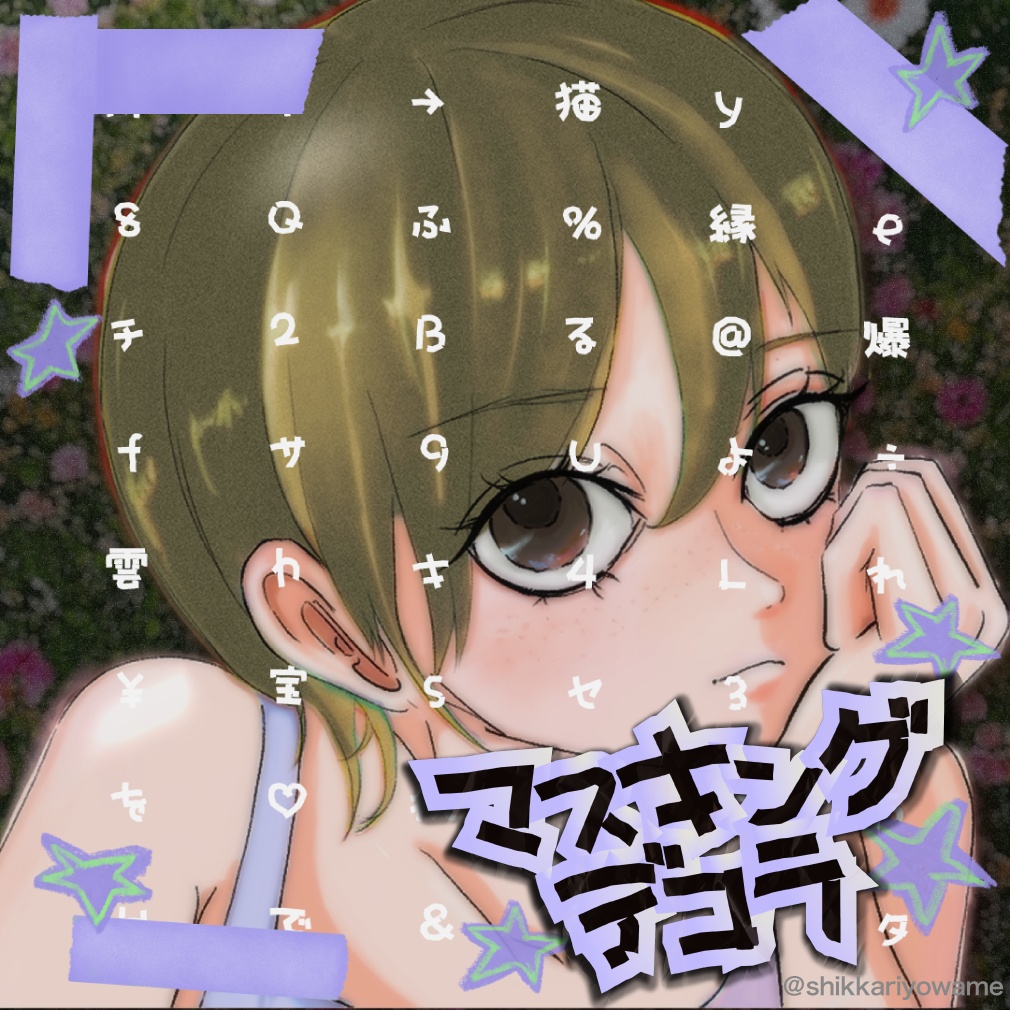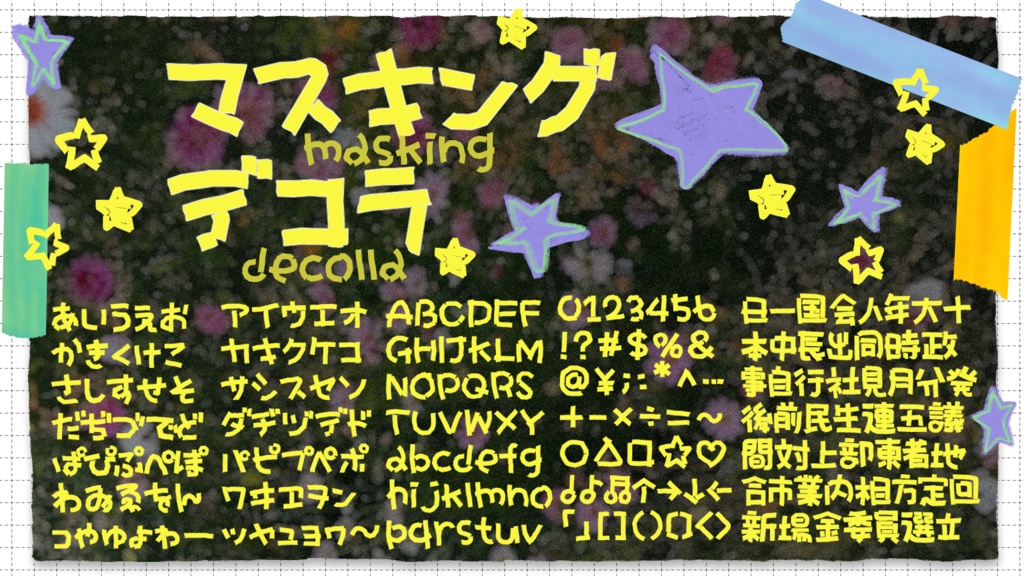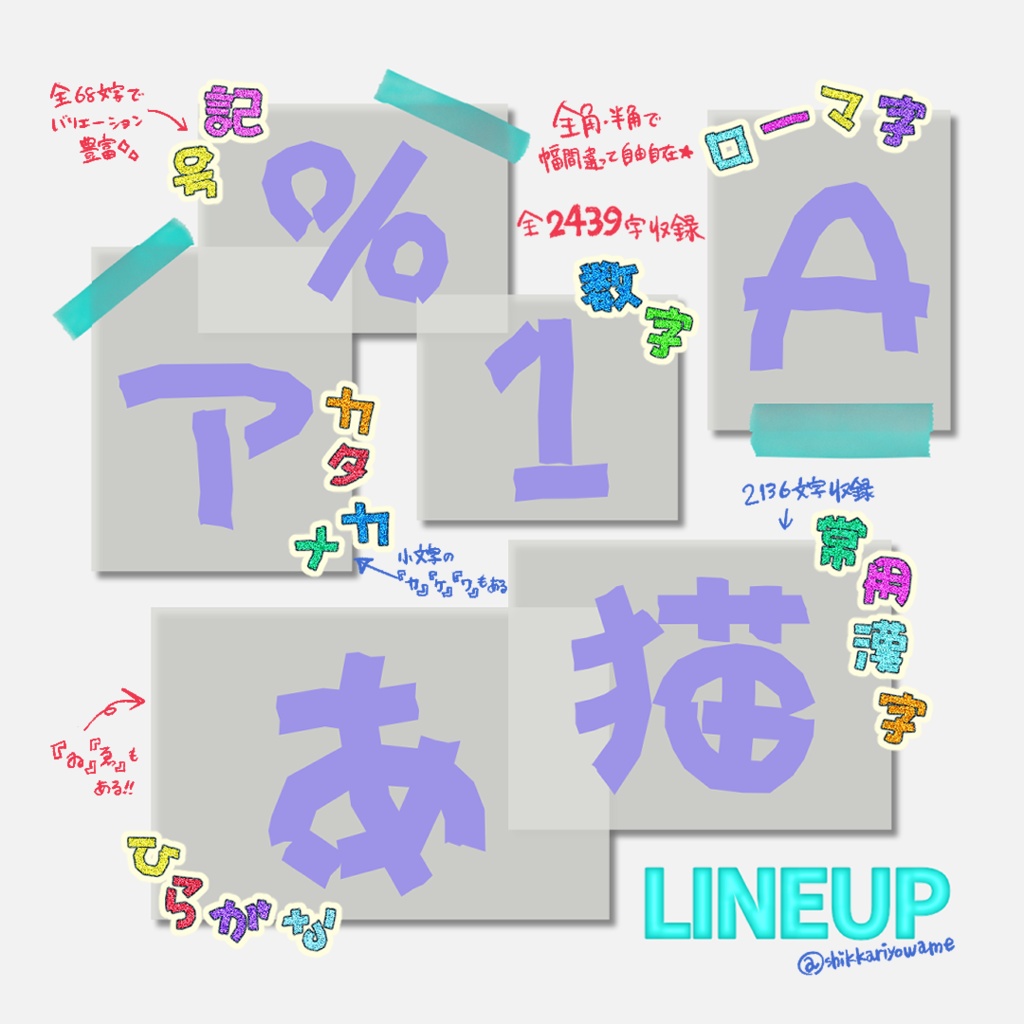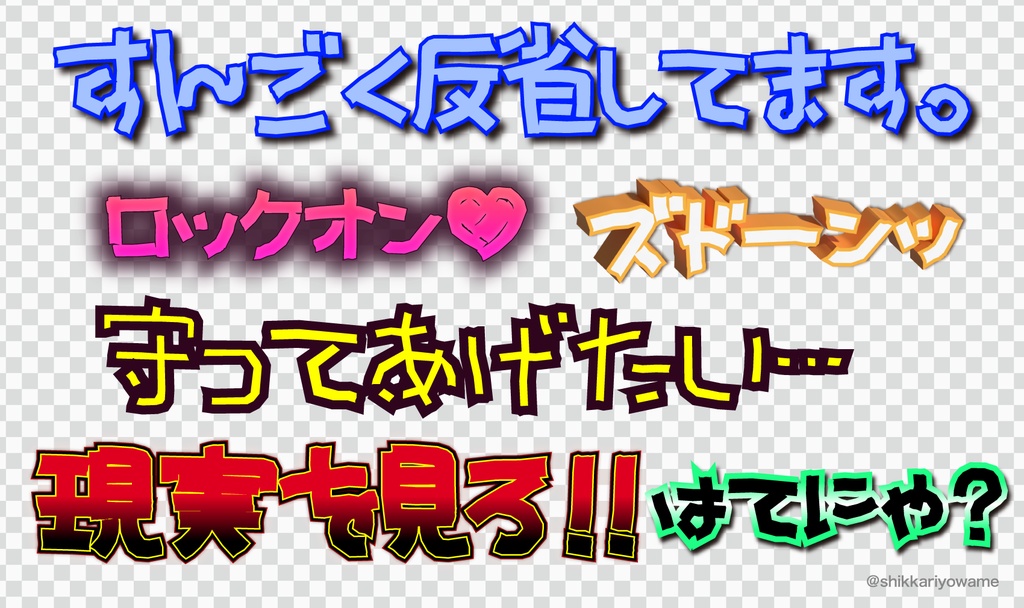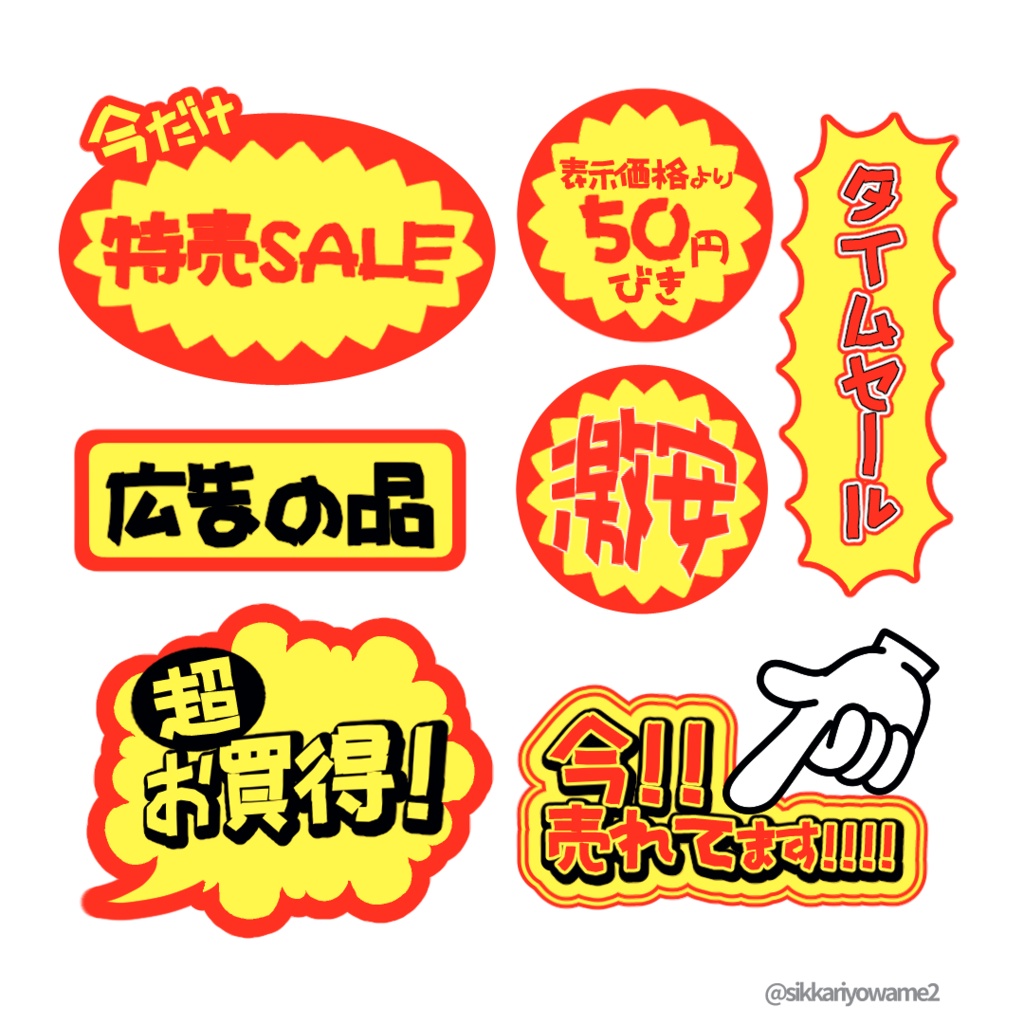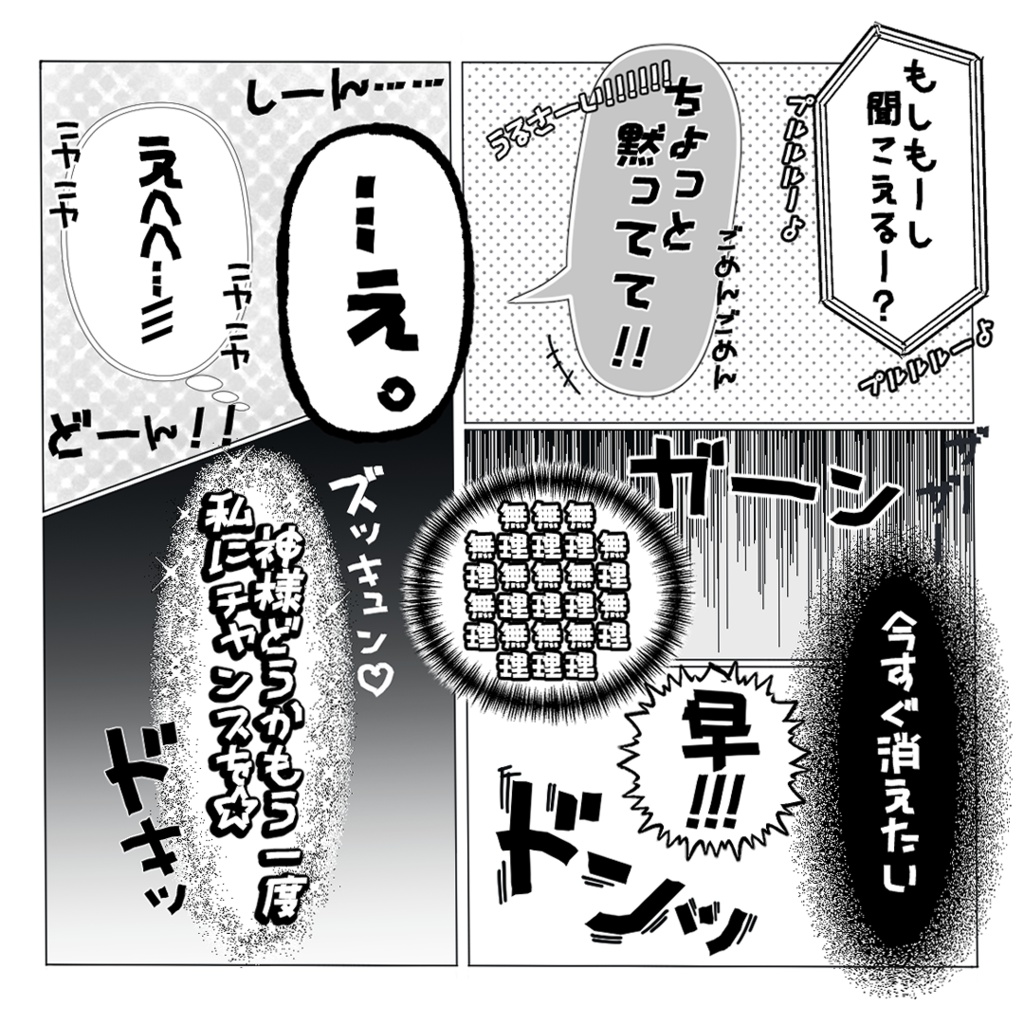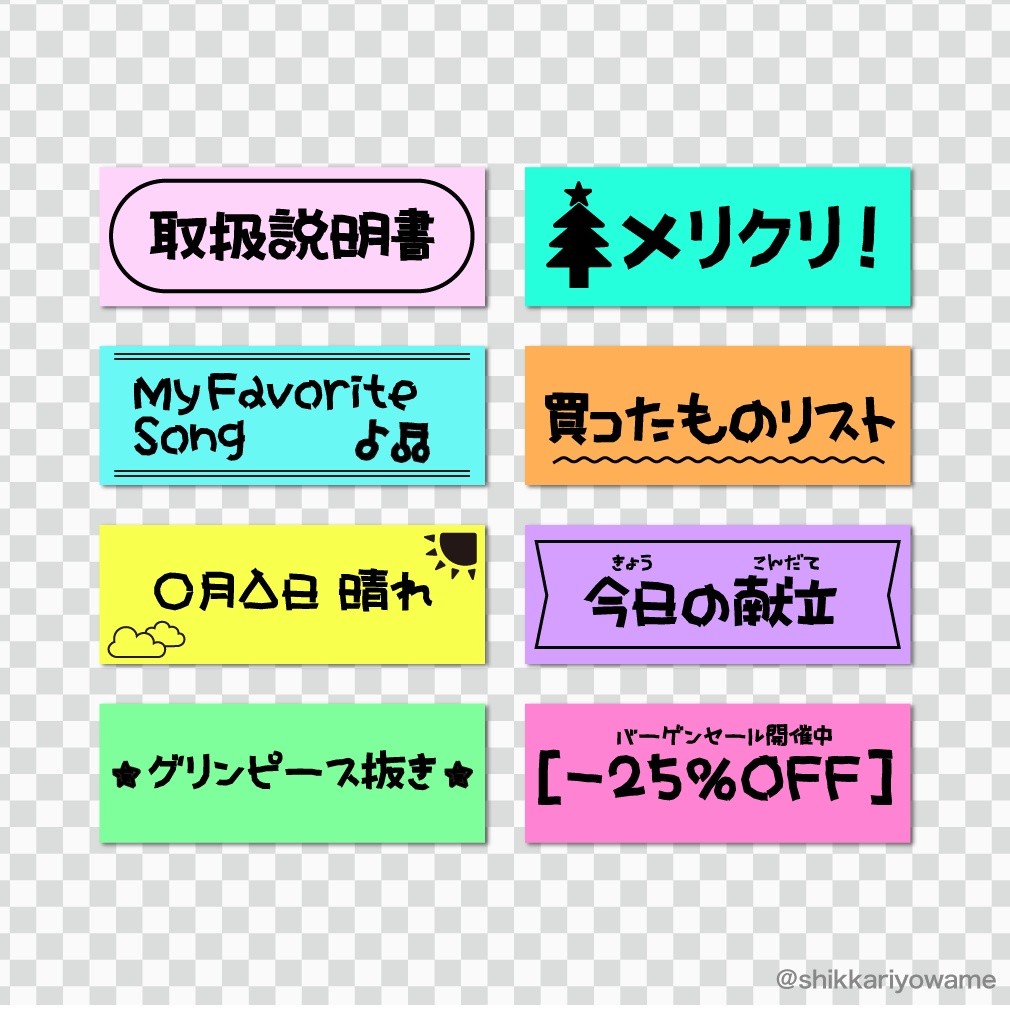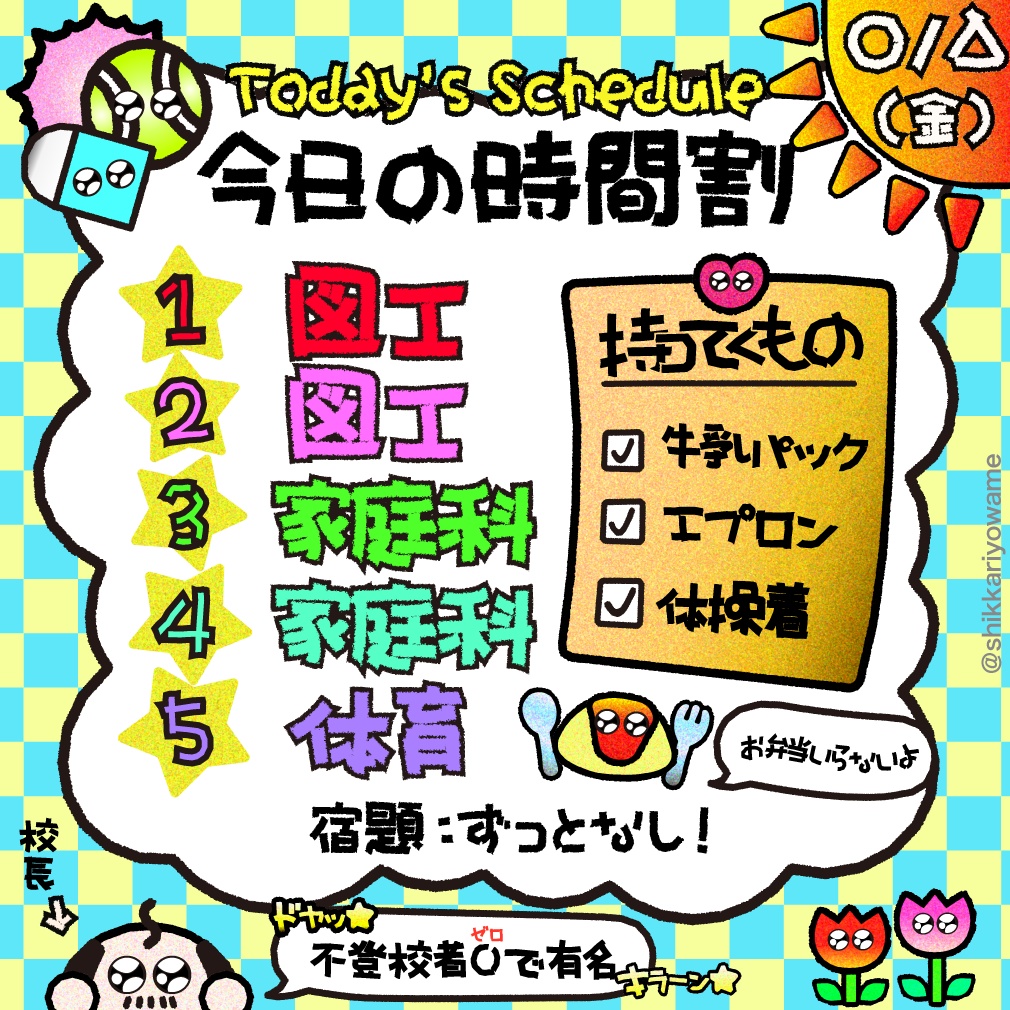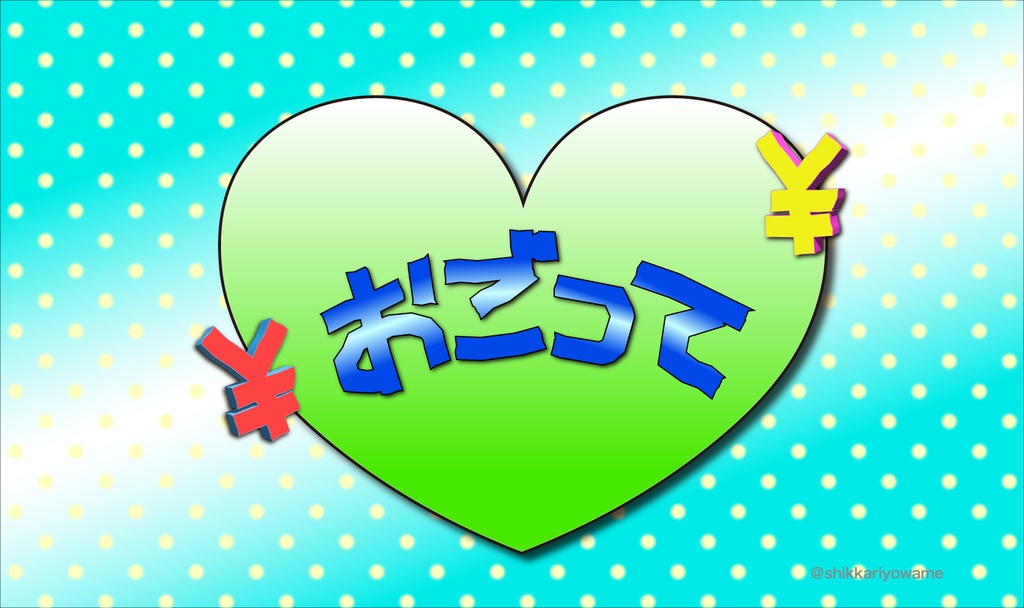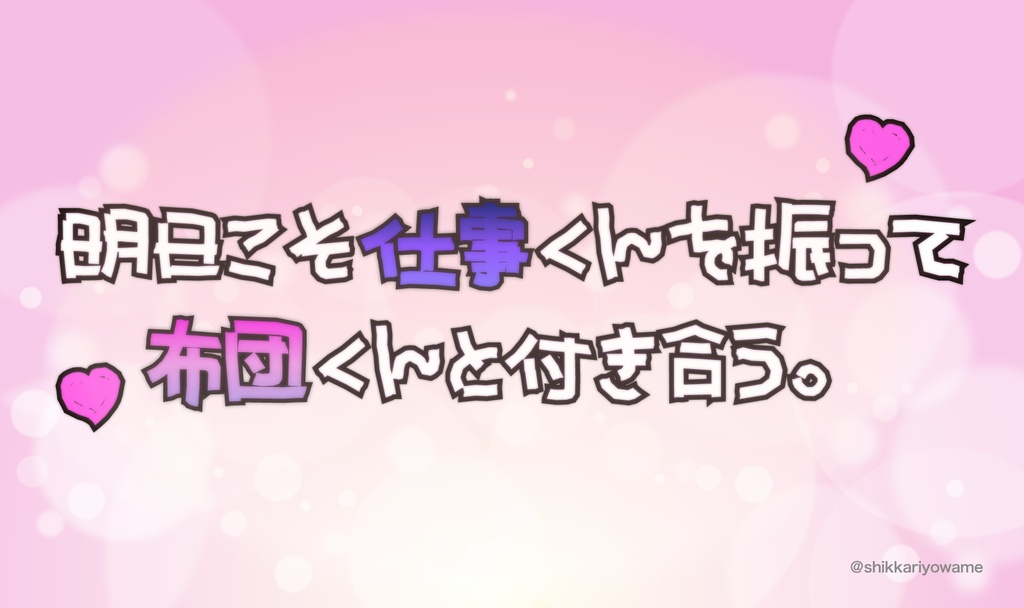
マスキングデコラ【フリーフォント】
“マスキングデコラ”/"Masking Decolla"フォント Xアカウント( https://x.com/shikkariyowame2 )をフォローでどなたでもDL可! 商用利用可能 【概要】 マスキングテープでペタペタ貼り付けて作ったようなコラージュ感が一気に増してカワイイ、創作意欲が湧く便利なフォントです。 動画のテロップや字幕、サムネ、広告、漫画のセリフや擬音、ロゴのコラージュなど画面映えし、困ったときマスキングデコラフォントで一気に華やかになる優れたデザイン性です。 【収録内容】 ・利用規約 ・OTFフォント ・ひらがな 、カタカナ、数字、記号、アルファベット、常用漢字(+嬉、垢) 2439文字以上収録 ※(無料版はひらがな、カタカナ、数字) 【無料版について】 無料版はひらがな、カタカナ、数字が収録されたフォントです。 Xアカウント( https://x.com/shikkariyowame2 )をフォローでどなたでもDL可能です。 【利用規約】 商用利用可能です。 (ご依頼での使用、ロゴ、映像、電子書籍、ゲーム、成人向け作品での使用、変形・加工も可能) 著作権は放棄しておりません。 フォントファイルの無断再配布、販売、譲渡、商標登録は禁止です。 (商標登録は加工した画像は可) 当フォントの使用に関連して生じたいかなる損害、トラブルは作者は責任を負いません。自身の責任でご使用ください。 詳細はフォントファイルと一緒に規約テキストを同梱しておりますので、そちらからご確認お願いします。 (※ https://lit.link/shikkariyowame からもご確認いただけます) ※フォント更新 2026/09/11 大改良 →空グリフの削除(未収録フォントの代替表示が可能) →フォント名を日本語表記 →スタイル名の変更(1→free/2→Regular) →フォントの埋め込みをインストール可(技術的ロックがなくなり、あらゆるファイル形式でトラブルなく使える)